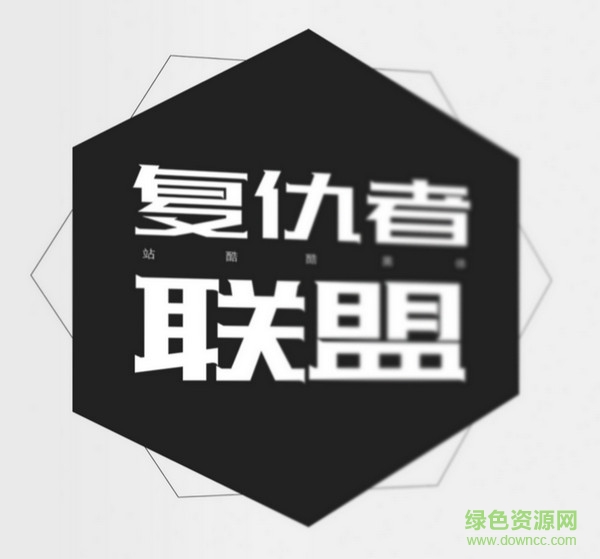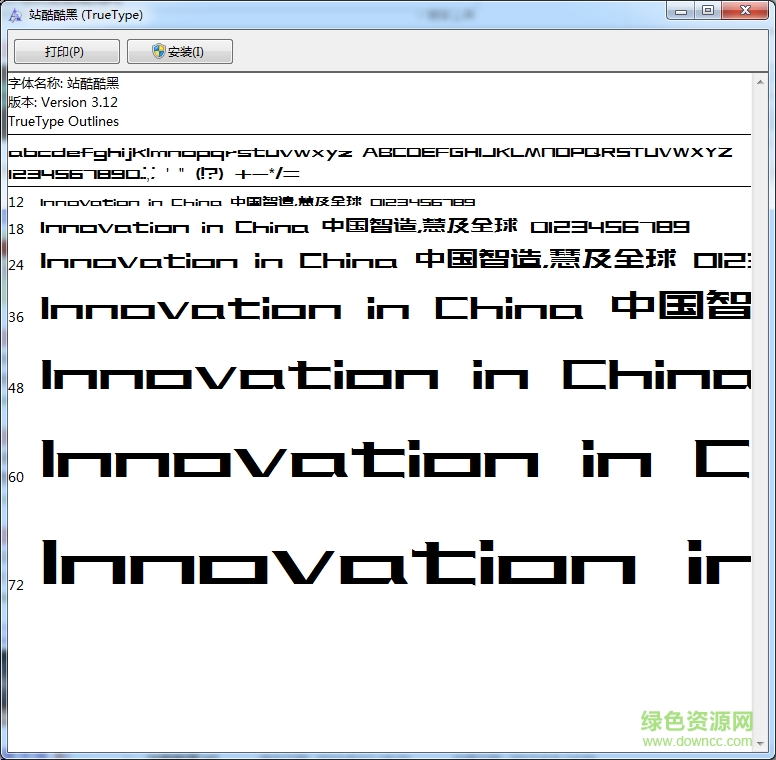
軟件介紹 軟件標簽: 站酷字體 字體 站酷酷黑體字體是站酷字體中非常常用的電腦字體軟件,字體線條流暢,簡潔大方行云流水,使用領域廣泛一鍵安裝便可快速使用??靵砭G色資源網下載體驗吧!站酷酷黑體介紹站酷酷黑體是站酷網推出的中文字體,站酷酷黑體驗版在站酷十周年之際橫空出世。字形筆畫粗獷有力,用寬扁型的字面構建出厚重的字體形態(tài),筆畫細節(jié)上的修飾既增強了字體的設計感,又讓字體多了一些小小的精致感,中宮的飽滿使得文字之間的排版組合非常醒目好看,有需要的下載吧!站酷酷黑體安裝解壓后,打開ttf字體文件。點擊安裝,安裝完成就可以使用了。 軟件截圖 上一張下一張(1 / 1) 安裝詳細截圖 其他版本下載 標題 大小 更新日期 下載 下載地址 電腦版 站酷酷黑體字體 官方版 點擊報錯 軟件無法下載或下載后無法使用,請點擊報錯,謝謝! 關閉報錯反饋 請描述您所遇到的錯誤,我們將盡快予以修正,謝謝! *必填項,請輸入內容 本類最新 dreamweaver字體庫 首爾南山體字體 v1.06 官方版 潮字社風云簡ttf 潮字社凌渡鯤鵬簡體字體 潮字社曾玉波手書簡字體 微博慧心字體 相關文章 Photoshop字體安裝使用方法和技巧 如何解決“無法新增字體”問題 Win 7系統(tǒng)安裝字體方法 網頁字體大小設置方法 怎么改網頁字體大小 在Linux系統(tǒng)中安裝字體的幾種方法 windows7字體顯示問題:打開某些程序的時候顯示的是亂碼 用戶評論 熱門評論 最新評論 發(fā)表評論 查看所有評論(0) 昵稱: 請不要評論無意義或臟話,我們所有評論會有人工審核. 字數(shù): 0/500 (您的評論需要經過審核才能顯示)